Chcieliśmy dać Ci kilka opcji ulepszenia własnej kolekcji czcionek o bardziej doskonałe i profesjonalne czcionki. W tym poście przedstawiamy starannie dobrany wybór najlepszych nowoczesnych czcionek, których możesz używać w swoich kreatywnych projektach i pracy z klientami.
Kolekcja obejmuje czcionki szeryfowe, skryptowe i bezszeryfowe o różnych stylach. Gwarantujemy, że na naszej liście znajdziesz więcej niż kilka czcionek, które warto pobrać. Spójrz.
01. FLIX – Nowoczesne logo i czcionka wyświetlacza
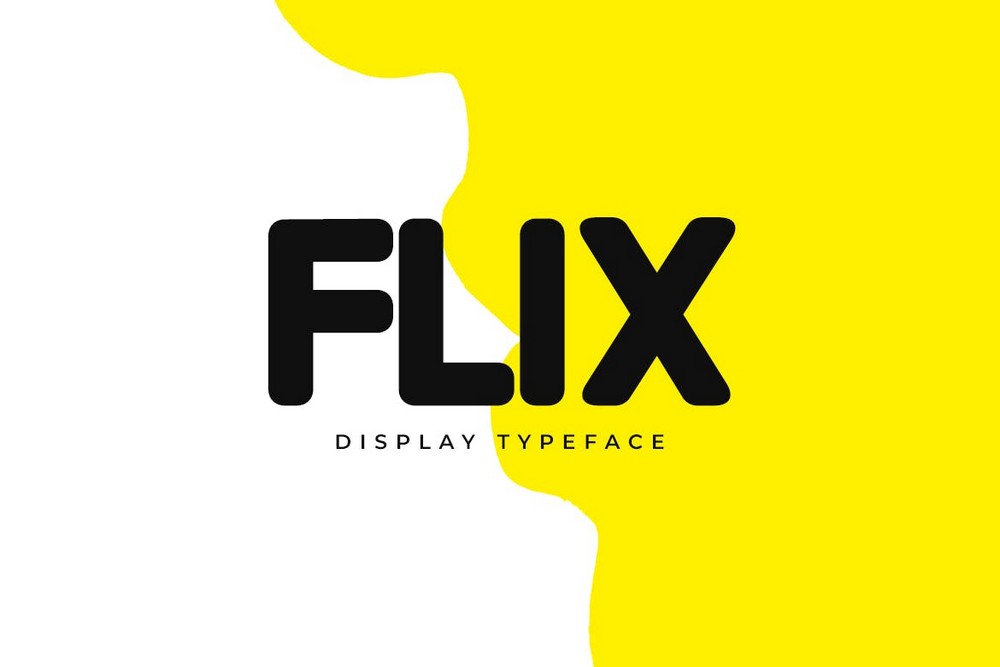
Jeśli szukasz czcionki o nowoczesnym wyglądzie do tworzenia logo, nagłówków witryn internetowych i tytułów plakatów, ta czcionka jest dla Ciebie idealna. Gładki wzór litery z zakrzywionymi krawędziami nadaje tej czcionce wyjątkową tożsamość. Występuje w dwóch stylach o regularnych i konturowych wzorach.
02. Devant Pro — nowoczesna czcionka bezszeryfowa
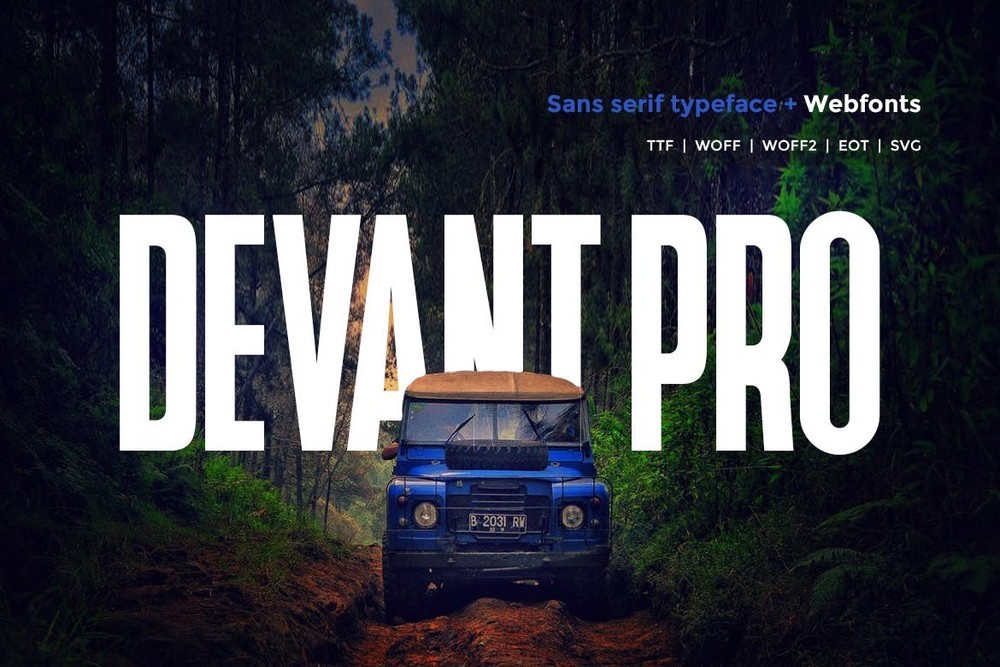
Wysoka i wąska konstrukcja tej czcionki sprawia, że jest to jedna z najlepszych czcionek, których można używać do tworzenia pogrubionych tytułów i nagłówków we wszystkich rodzajach druków i projektów cyfrowych. Występuje w wielu formatach, w tym w wersjach SVG i WebFont.
03. Ace Sans – rodzina czcionek bezszeryfowych
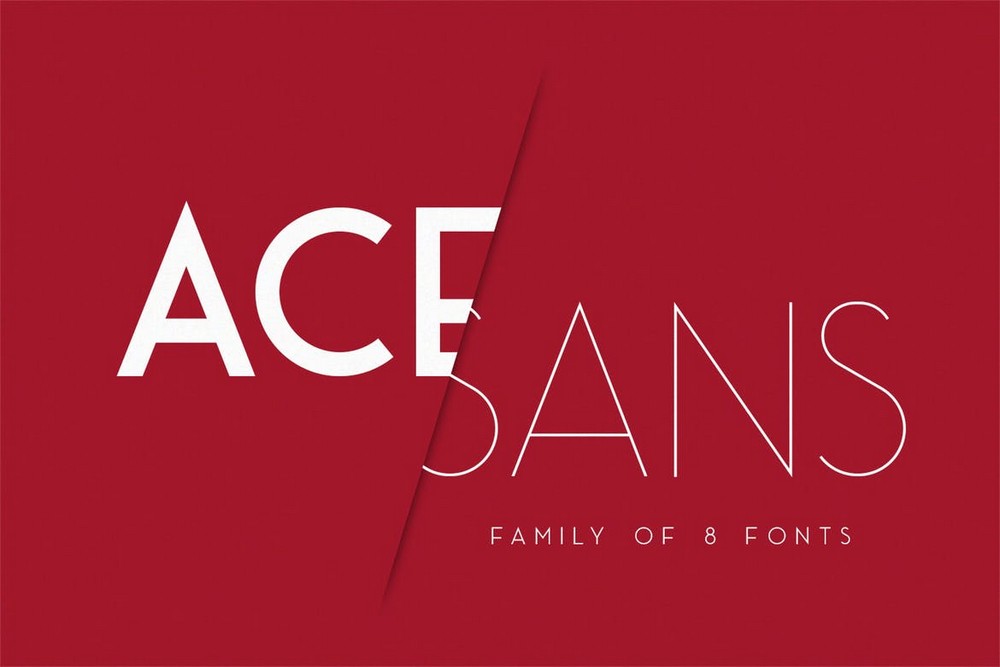
Ace Sans to kompletna rodzina czcionek bezszeryfowych. Zawiera 8 różnych grubości czcionek, od cienkich do bardzo pogrubionych. Pozwoli Ci mieszać i dopasowywać różne grubości czcionek, aby tworzyć unikalne tytuły, a także używać ich do akapitów.
04. Monolith – rodzina czcionek Thin Sans
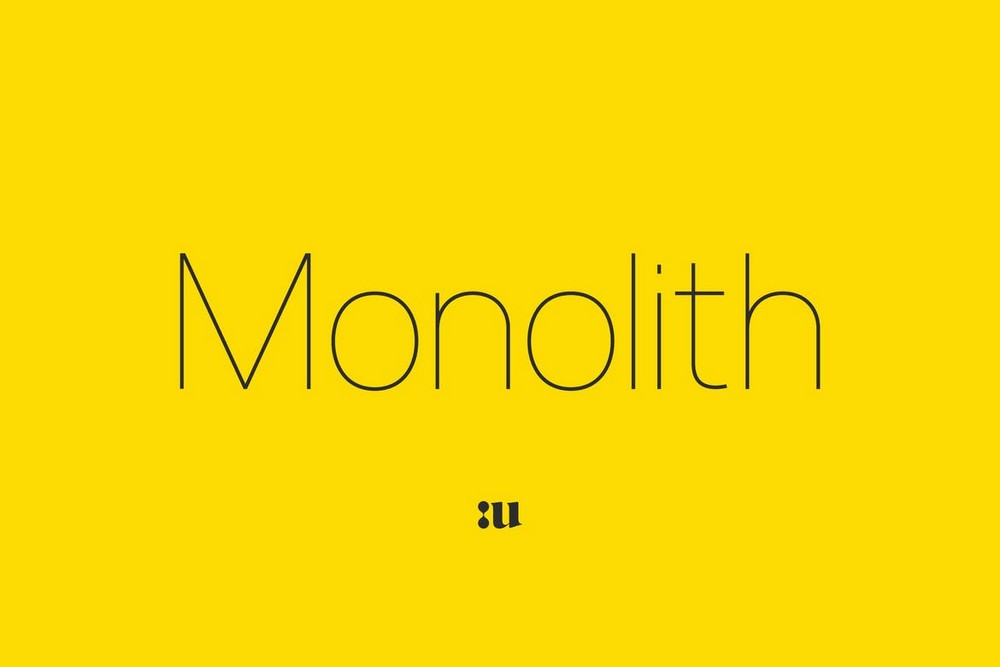
Stylowo cienka konstrukcja tej czcionki bezszeryfowej nadaje jej elegancki wygląd, w przeciwieństwie do innych czcionek na naszej liście. Jest idealny do projektowania logo, tytułów i nagłówków dla nowoczesnych projektów biznesowych i profesjonalnych. Czcionka występuje w 2 grubościach i dopasowanych wersjach kursywy.
05. Dastend – modny krój pisma
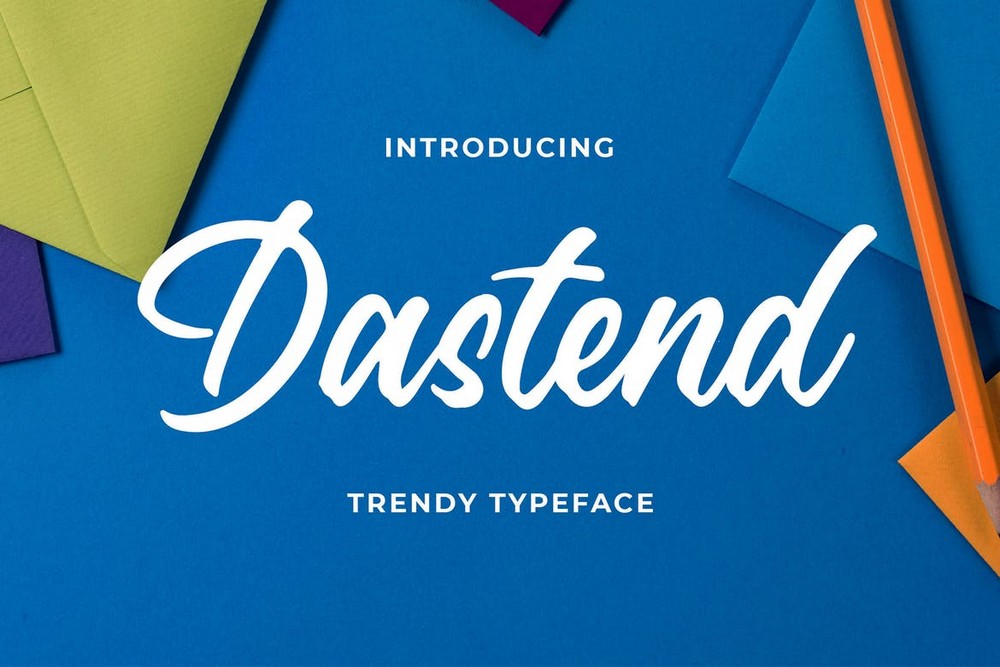
Dastend to stylowa czcionka skryptowa, której można używać do projektowania różnych projektów drukowanych i cyfrowych. Jest najbardziej odpowiedni do tworzenia kart okolicznościowych, wizytówek i postów w mediach społecznościowych. Czcionka zawiera zarówno wielkie, jak i małe litery.
06. Cleon – elegancka czcionka bezszeryfowa
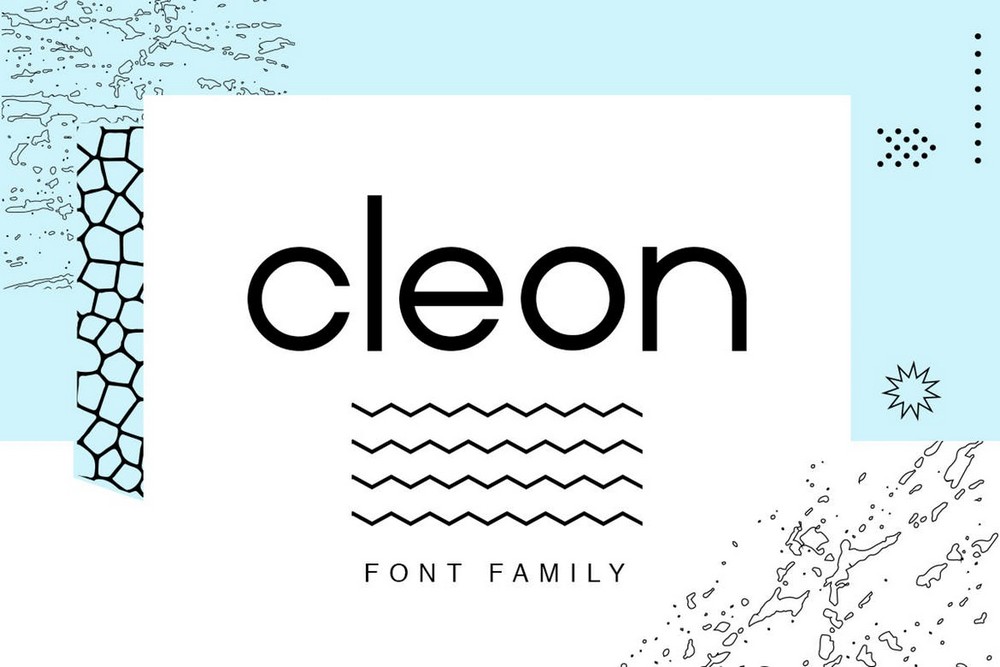
Na pierwszy rzut oka ta czcionka przypomina popularne marki i logo lifestylowe. To dlatego, że ma elegancki wygląd, powszechnie spotykany w nowoczesnych projektach. Idealnie nadaje się do projektowania logo, oznakowania, etykiet i nie tylko.
07. Bjola – kreatywna czcionka bezszeryfowa
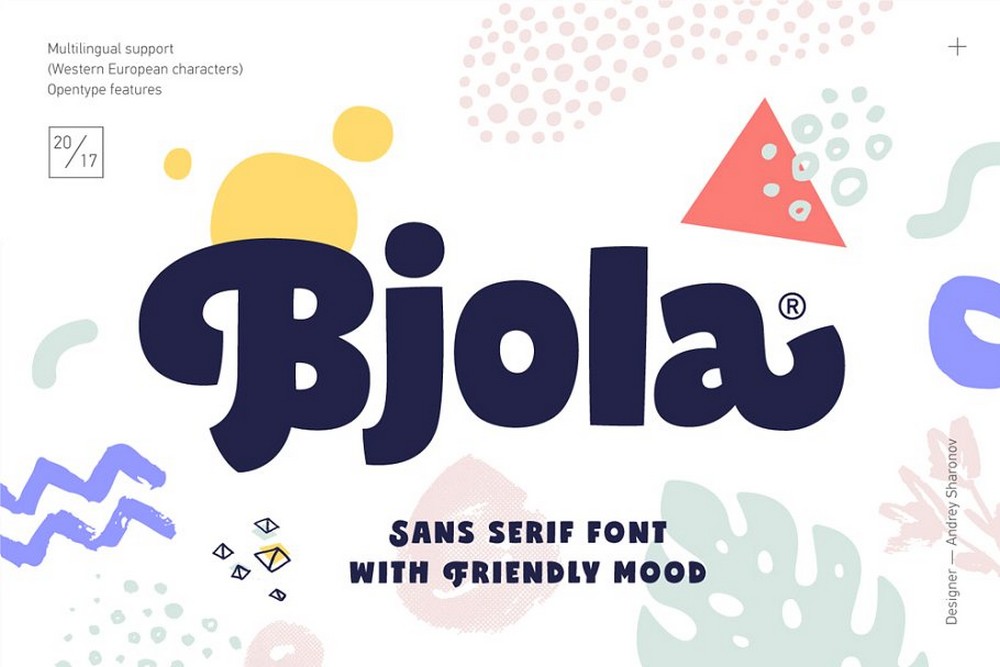
Jeśli pracujesz nad zabawnym i kreatywnym projektem, ta stylowa czcionka bezszeryfowa z pewnością pomoże dodać charakteru Twojemu projektowi. Jest wyposażony w piękny i zabawny projekt czcionki zawierający zarówno wielkie, jak i małe litery. Jest idealny do projektów kart okolicznościowych i plakatów.
08. Bulgis – stylowa czcionka skryptowa
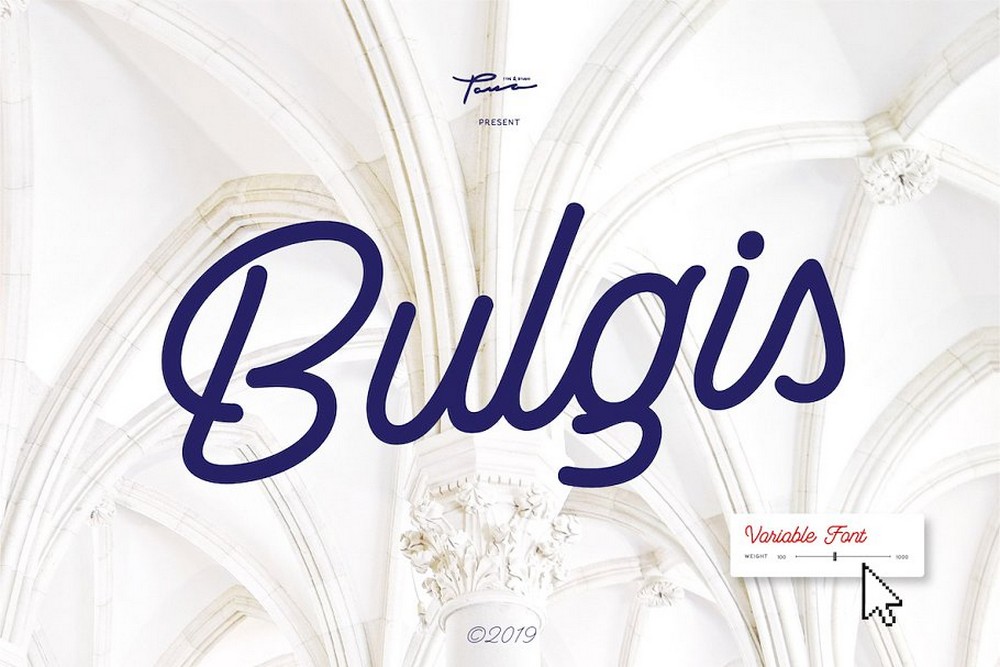
Elegancka czcionka o nowoczesnym designie. To tylko czcionka, której będziesz potrzebować do tworzenia kart okolicznościowych, wizytówek, postów w mediach społecznościowych i wielu innych. Czcionka jest dostępna w wielu grubościach, w tym grubościach cienkich i pogrubionych. Obejmuje również ligatury i znaki kaligraficzne.
09. Hazel – elegancka czcionka w stylu art deco
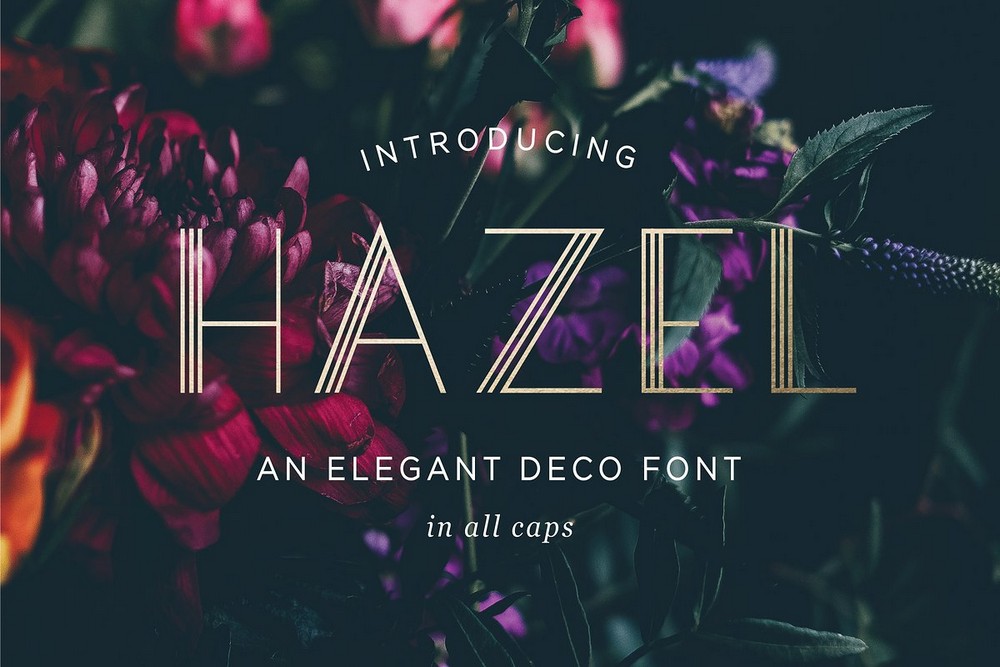
Ta wyjątkowa czcionka łączy w sobie nowoczesne i klasyczne elementy stylu art-decon. Zawiera zestaw liter pisanych wielkimi literami. Idealnie nadaje się do projektowania tytułów i nagłówków nowoczesnych plakatów, ulotek oraz okładek książek lub płyt CD.
10. Visby CF – geometryczna czcionka Sans
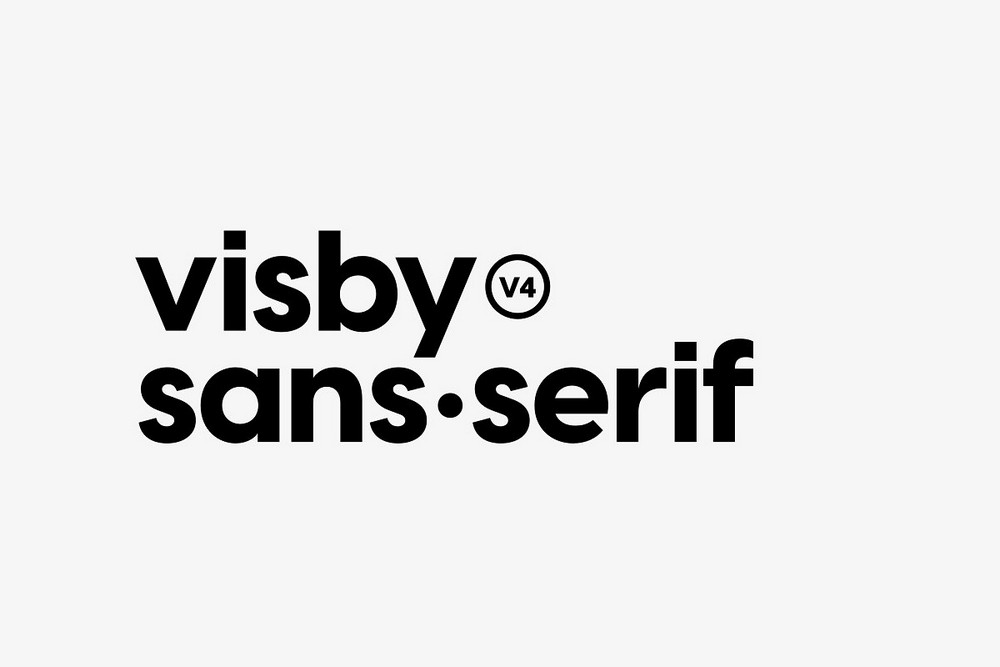
Visby CF to prosta rodzina czcionek. Nie ma żadnych fantazyjnych wzorów, krzywizn ani zaokrąglonych krawędzi. To po prostu nowoczesna standardowa czcionka. To sprawia, że jest to doskonały wybór do projektowania tekstu akapitowego. To znacznie poprawi czytelność.
11. Hello Paris – Nowoczesna para czcionek
Znalezienie odpowiedniej pary czcionek do projektów projektowych to jedna z rzeczy, z którymi boryka się większość projektantów. Ale korzystając z tego pakietu czcionek, nie musisz się o to martwić. Ten pakiet czcionek zawiera parę czcionek. Zawiera parę czcionek szeryfowych i pisma ręcznego, które po prostu idealnie razem wyglądają.
12. Botanica – nowoczesny zestaw czcionek i logo
To nowoczesna czcionka, której możesz użyć do projektowania unikalnych logo i nagłówków witryn dla kreatywnych firm. W rzeczywistości jest nawet wyposażony w zestaw logo z 8 edytowalnymi szablonami logo wektorowego. Korzystając z tego zestawu czcionki + logo, możesz uzyskać przewagę w procesie projektowania logo.
13. Maxine — elegancka czcionka bezszeryfowa
Maxine to elegancka czcionka bezszeryfowa, która idealnie nadaje się do tworzenia nowoczesnych logo dla kreatywnych firm i agencji. Czcionka ma różne grubości i zawiera zarówno wielkie, jak i małe litery.
14. Blackpool — odręczna czcionka skryptu
Jeśli pracujesz nad projektem związanym z fotografią, modą lub stylem życia, ta piękna czcionka przyda się. Charakteryzuje się unikalnym, odręcznym wzorem, który idealnie pasuje do nowoczesnych marek i firm lifestylowych. To także świetny wybór do projektowania wizytówek i kart okolicznościowych.
15. Grandon – geometryczna czcionka Sans
Twórz odważne i atrakcyjne tytuły swoich plakatów i banerów, używając tej nowoczesnej czcionki. Charakteryzuje się geometrycznie dokładnym projektem litery, stworzonym specjalnie do pracy zawodowej. Czcionka ma różne grubości i zawiera zarówno wielkie, jak i małe litery.
16. Styl trybu – Modern Font Duo
Kolejny duet czcionek, który idealnie nadaje się do projektowania różnych nowoczesnych i kreatywnych projektów. Pakiet zawiera dwie czcionki z czcionką bezszeryfową i czcionką w stylu podpisu, które dobrze ze sobą współgrają. To idealne połączenie dla projektów marek modowych i lifestylowych.
17. Dziewczęca miłość – nowoczesna czcionka skryptowa
Girly Love to stylowa czcionka skryptowa, której można używać do projektowania zaproszeń ślubnych, kart okolicznościowych i różnych kobiecych projektów. Projekt czcionki sprawia, że jest to również świetny wybór do tworzenia logo. Obejmuje również ligatury i obsługę wielu języków.
18. Zona Pro – nowoczesna rodzina czcionek Sans
Zona Pro to rodzina czcionek bezszeryfowych, która obejmuje ponad 18 różnych stylów i grubości czcionek, od pogrubionych do cienkich. Ta czcionka jest odpowiednia do wszystkiego, od tytułów plakatów po projekty opakowań, logo, nagłówki stron internetowych i wiele innych.
19. Gilroy – nowoczesna profesjonalna czcionka
Gilroy to kreatywna rodzina czcionek z 20 różnymi stylami czcionek. Pochodzi z drogą metką. Ale możesz kupić ciężarki pojedynczo w niskiej cenie. Ta czcionka jest idealna do projektowania tytułów i nagłówków na nowoczesnych stronach internetowych.
20. Campora – Nowoczesna czcionka logo i tytułu
Jeśli szukasz inspiracji do zaprojektowania logo dla nowoczesnej marki lub tytułu plakatu, ta czcionka jest idealnym miejscem na rozpoczęcie. Posiada unikalny projekt liter, który pozwoli Ci stworzyć atrakcyjne logo, banery i plakaty. Czcionka zawiera również wiele grubości.